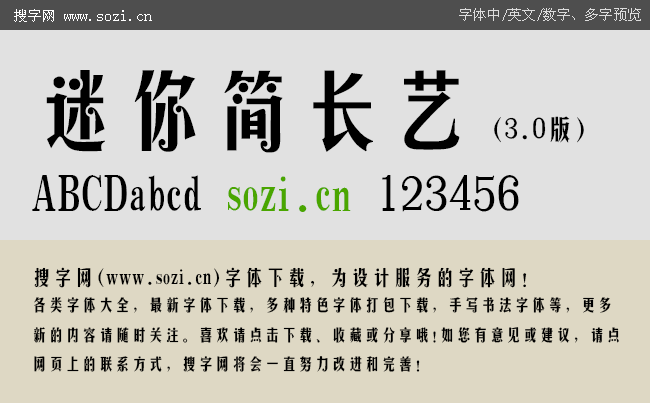
迷你簡長藝
搜字網(wǎng)給大家提供一款迷你簡長藝中文藝術(shù)字體下載。迷你簡長藝體筆畫既有黑體的粗壯醒目,又有宋體的秀美柔和,加上藝術(shù)性的圓球形點、起筆如蝌蚪形的頓點、螺螄轉(zhuǎn)似的小鉤,配以修長的字形,如少女般婷婷玉立,裊娜動人,美觀而不落俗套。適合標題、廣告、兒童讀物使用。